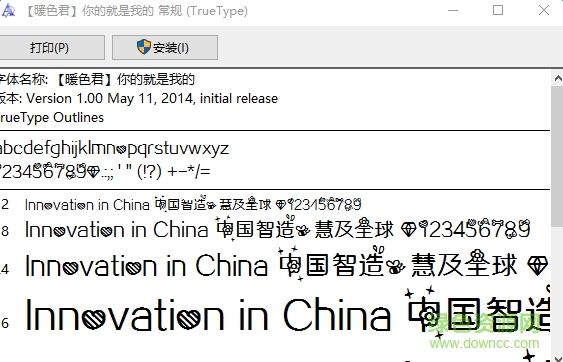
你的就是我的
你的就是我的字體是一款很好看的電腦藝術(shù)字體,正是因?yàn)檫@款字體是具有藝術(shù)風(fēng)格的,所以用于藝術(shù)設(shè)計(jì)、廣告設(shè)計(jì)等都是很不錯(cuò)的,大家如果喜歡這款字體可以隨時(shí)來(lái)綠色資源網(wǎng)下載。
你的就是我的字體
你的就是我的字體是一款很有意思的字體,其獨(dú)特的藝術(shù)魅力讓很多年輕人都喜歡它,如果你也喜歡,那就快來(lái)綠色資源網(wǎng)下載吧。